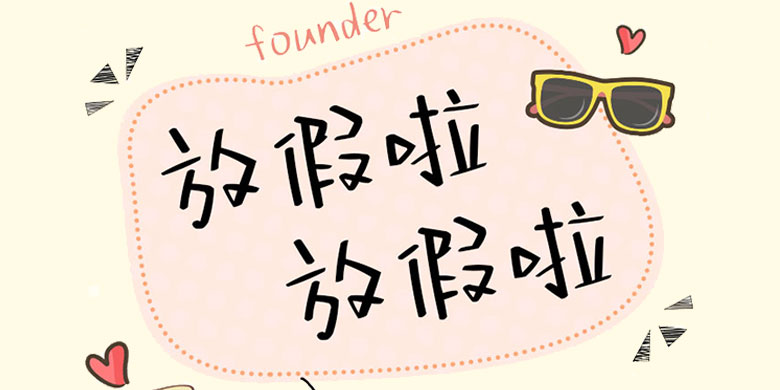
方正手迹-放假啦放假啦
品牌:方正手迹设计师:俞亦婷发行时间:2019字库编码:大陆简体(GB2312-80)分类:创意书写字体属性:精品字
放假啦放假啦大胆采用了横画倾斜的字形特点,极具动感。笔画设计自由度较高,灵活多变,使放假啦放假啦灵动飘逸,极具特色。适用于文化类的宣传设计,以及商业类品牌的广告和产品包装设计。